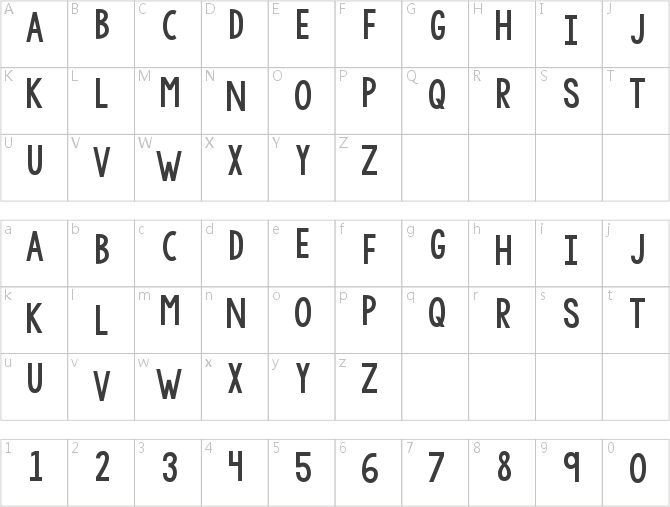
KG Sorry Not Sorry Chub 详情页
KG Sorry Not Sorry Chub
KG Sorry Not Sorry Chub字体字库是一款让人赏心悦目、百看不厌的英文字体,适合各类广告和产品包装设计应用,字体大小0.03MB,格式为ttf字体,上传用户是IceNet,作者/版权方为未知